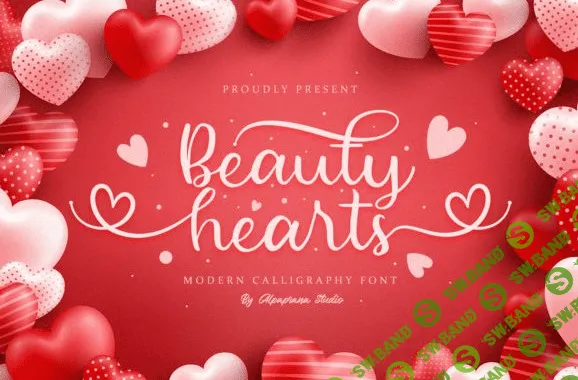
Название: Beauty Hearts Font
Это потрясающий и милый рукописный шрифт с аутентичным чувством.
Он будет прекрасно использоваться для брендинга, дизайна логотипов, одежды, плакатов и многого другого.